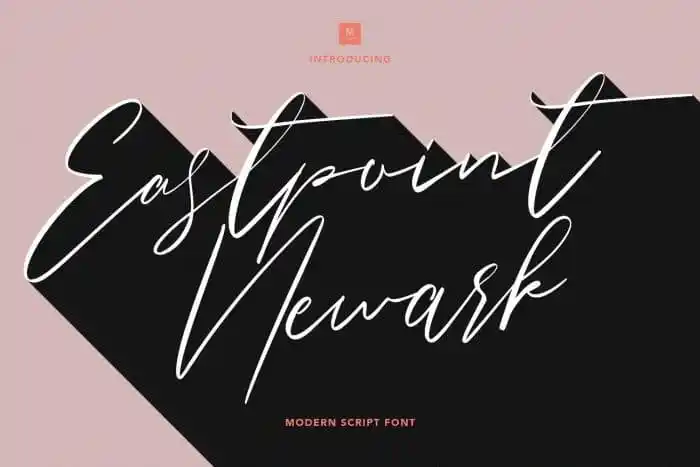
Eastpoint Script Font – Download Grátis
Eastpoint Script Font é uma elegante fonte de estilo moderno e angelical, cuidadosamente desenvolvida pelo Maulana Creative na plataforma 99designs. Com sua tipografia suave e refinada, essa fonte perfeita se adapta a diversas necessidades gráficas, como assinaturas, cartões de papelão, logotipos, citações em revistas ou livros, cabeçalhos de sites, panfletos, roupas, marcas de marca e embalagens. Suavemente delicada mas com um toque de modernidade, Eastpoint Script Font torna-se uma escolha ideal para designers que buscam um toque único em seus projetos visuais.